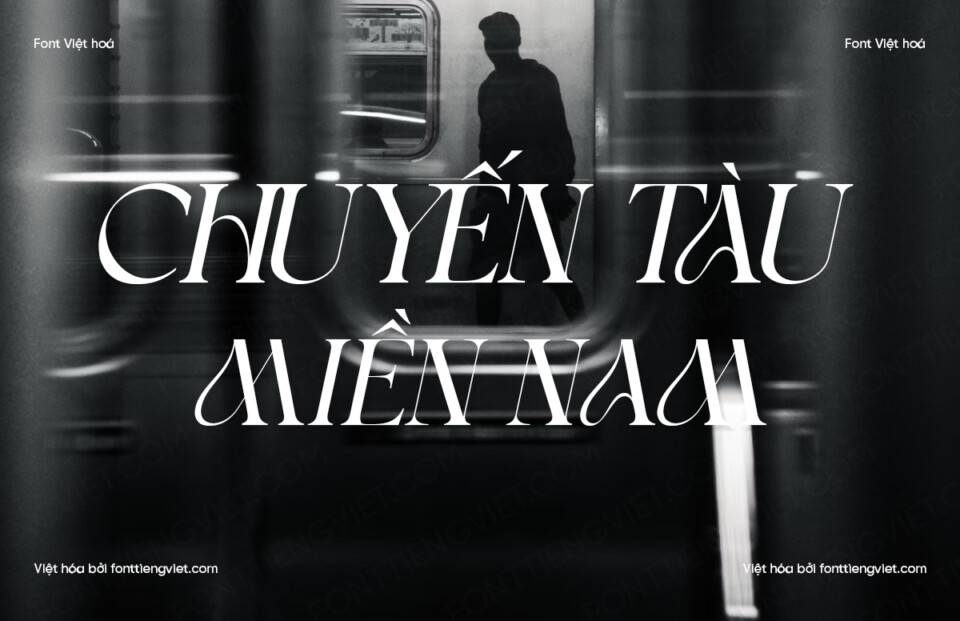
Font Việt hóa 1FTV VIP Lamoric Rowen Italic
Font Việt hóa 1FTV VIP Lamoric Rowen Italic – Lựa chọn hoàn hảo cho thiết kế sang trọng
Giới thiệu về Font Việt hóa 1FTV VIP Lamoric Rowen Italic
Trong thế giới thiết kế đồ họa hiện đại, việc tìm kiếm một bộ Font Miễn Phí chất lượng cao và hỗ trợ đầy đủ tiếng Việt luôn là ưu tiên hàng đầu của các designer. Font Việt hóa 1FTV VIP Lamoric Rowen Italic nổi lên như một hiện tượng nhờ sự kết hợp tinh tế giữa nét chữ cổ điển và phong cách hiện đại đầy lôi cuốn. Đây là một phông chữ thuộc phân khúc VIP, được chăm chút kỹ lưỡng từng đường nét nghiêng (italic) để tạo ra sự chuyển động mềm mại nhưng vẫn giữ được cấu trúc vững chãi. Với bộ font này, người dùng tại Việt Nam có thể dễ dàng truyền tải những thông điệp nghệ thuật mà không lo ngại về vấn đề lỗi font hay thiếu dấu tiếng Việt đặc trưng.
Đặc điểm nổi bật của Font Việt hóa 1FTV VIP Lamoric Rowen Italic
Phong cách thiết kế quý tộc và thanh lịch
Đúng như tên gọi “VIP”, Font Việt hóa 1FTV VIP Lamoric Rowen Italic sở hữu những đường nét thanh mảnh, bay bổng. Điểm nhấn chính nằm ở độ nghiêng hoàn hảo, giúp các con chữ trông như đang lướt đi trên mặt giấy. Sự kết hợp giữa các nét dày và mỏng được tính toán tỉ mỉ, tạo nên một tổng thể hài hòa và vô cùng sang trọng. Điều này giúp bộ font trở nên cực kỳ phù hợp cho các dự án thiết kế cao cấp như thiệp mời đám cưới, bìa tạp chí thời trang hoặc các ấn phẩm quảng cáo mỹ phẩm. Mỗi ký tự trong bộ font đều toát lên vẻ chuyên nghiệp, giúp nâng tầm giá trị thẩm mỹ cho tác phẩm của bạn.
Khả năng tương thích và ứng dụng đa dạng
Dù mang phong cách nghệ thuật cao, nhưng 1FTV VIP Lamoric Rowen Italic lại có tính ứng dụng rất linh hoạt. Bạn có thể sử dụng nó làm tiêu đề chính để thu hút sự chú ý ngay lập tức, hoặc dùng làm các dòng chú thích (quote) đầy cảm hứng. Đặc biệt, nhờ quy trình Việt hóa chuyên nghiệp từ đội ngũ 1FTV, các dấu câu tiếng Việt được đặt ở vị trí chuẩn xác, không gây rối mắt và giữ nguyên được tinh thần gốc của bản thiết kế quốc tế. Điều này hỗ trợ tối đa cho các bạn học sinh, sinh viên khi làm báo cáo thuyết trình hoặc các giáo viên muốn trang trí bài giảng điện tử thêm phần sinh động và bắt mắt hơn.
Lợi ích khi sử dụng Font Việt hóa 1FTV VIP Lamoric Rowen Italic trong sáng tạo
Việc sử dụng Font Việt hóa 1FTV VIP Lamoric Rowen Italic không chỉ giúp tiết kiệm thời gian chỉnh sửa dấu mà còn mang lại sự đồng nhất cho toàn bộ dự án. Trong giáo dục, một phông chữ đẹp và dễ đọc sẽ kích thích thị giác, giúp người xem tiếp nhận thông tin nhanh chóng hơn. Đối với những nhà sáng tạo nội dung số, bộ font này là công cụ đắc lực để tạo ra các bộ nhận diện thương hiệu cá nhân độc đáo trên mạng xã hội. Sự mềm mại của biến thể Italic giúp cân bằng lại những khối bố cục khô cứng, tạo ra một không gian thiết kế giàu cảm xúc và đầy tính nhân văn.
Kết luận về bộ font nghệ thuật đỉnh cao